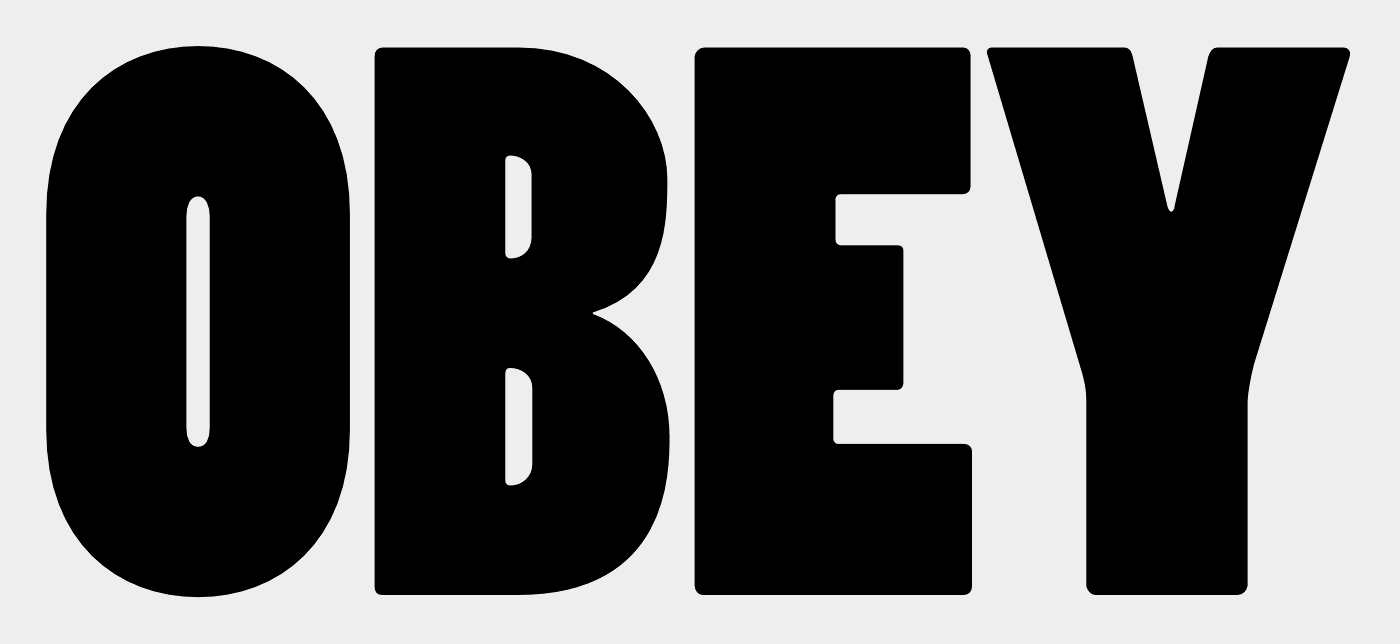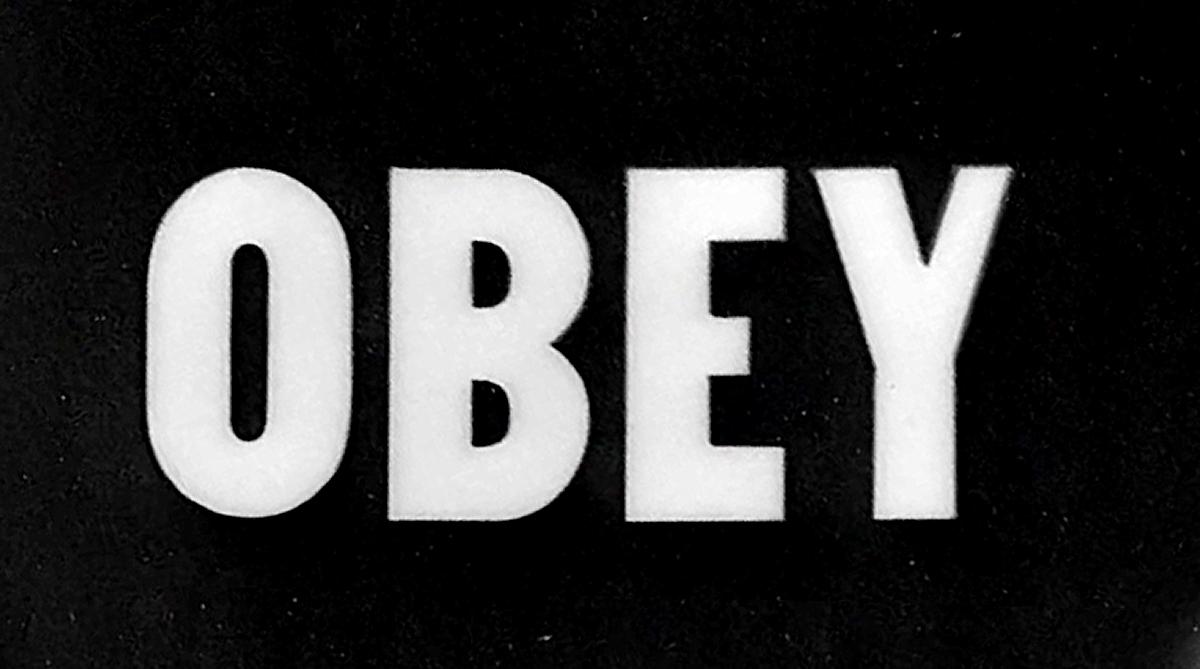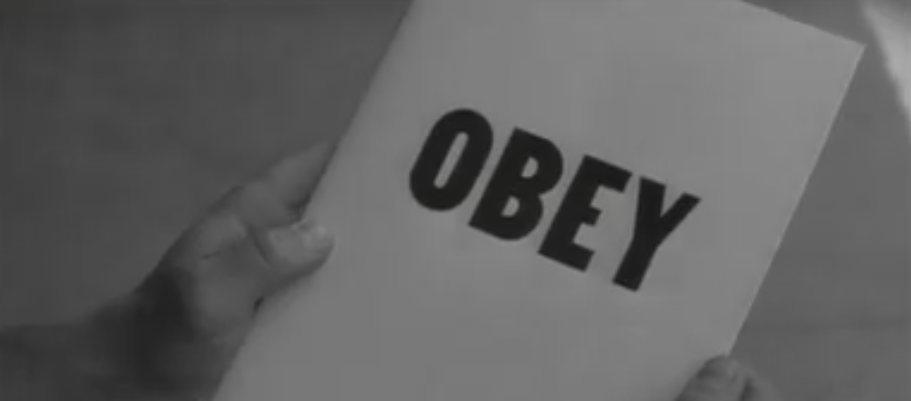
Bold Condensed Schrift
hat jemand eine Ahnung, um welche Schrift es sich hier handelt?
OBEY, kam das nicht in Carpenters »Sie leben« vor? Da waren Plakate mit getarnten Botschaften zu sehen wenn ich mich richtig erinnere.
Ich probiere mal die üblichen Verdächtigen Suchmaschinen durch.
1) What Font Is bringt keine sinnvollen Ergebnisse.
2) Fontspring liefert Classroom JNL von Jeff Levine:
3) What The Font bringt keine sinnvollen Ergebnisse.
Jetzt müsste man sich Classroom JNL näher ansehen.
A set of old die-cut cardboard letters and numbers used by teachers directly on bulletin boards or for tracing was the inspiration for Classroom JNL. In turn, these letters take their cue from typefaces such as Franklin and earlier wood type designs.
Die-cut? Ach je ... was ist das?
Sind das dann alte Prägebuchstaben gewesen? Hier in Wirtschaftswunderschland gibt es da viele von der DIN 1451 inspirierte Schriften, welche aber von Hersteller zu Hersteller verschieden sind und nicht als Satzschriften existieren. Na ja ... Sehr viel weiter komme ich damit also nicht. Aber ein bisschen Überblick gibt das schon?